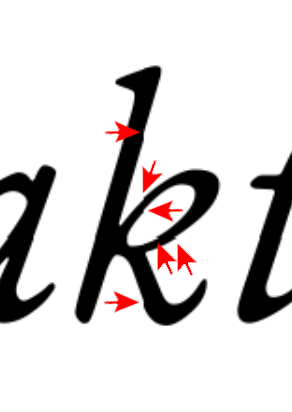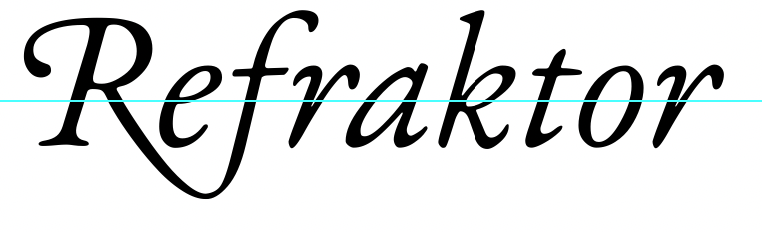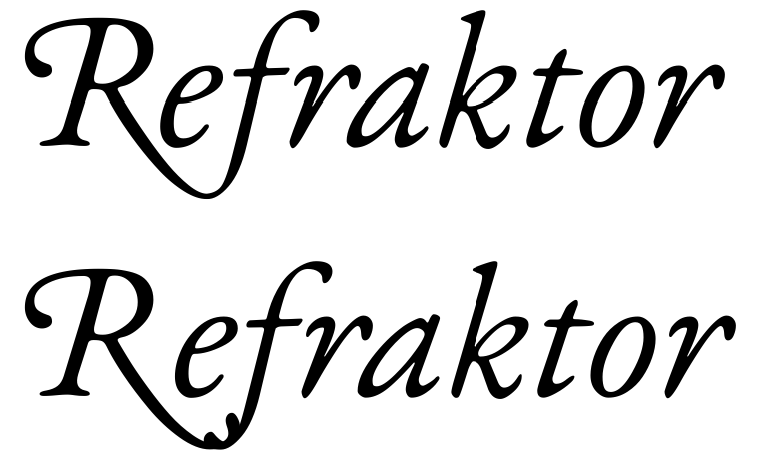
Ligatur über einen Buchstaben hinweg - geht sowas?
Ich bin bei einem Layout-Projekt auf ein interessantes Problem gestoßen. Ich setze in EBGaramond, habe für den Kursivsatz die geschwungenen Versalienvarianten gewählt und da kommen sie bei den Wörtern "Reflektor" und "Refraktor" das lange Bein des geschwungenen "R" und das kleine "f" in die Quere. Das sieht dann aus wie unten dargestellt.
Gelöst habe ich das Problem, indem ich fürs Erste für diese Konstellation das geschwungene "R" durch das normale kursive "R" ersetzt habe. Trotzdem gefiele mir die Idee einer eigenen Ligatur aus geschwungenem kursiven "R" und dem kursiven kleinen "f", die um das "e" herum geführt wird. Frage in die Runde: Gibt es sowas? Ist sowas denkbar? Oder sollte man sowas tunlichst bleiben lassen? Der EBGaramond-Code würde zumindest theoretisch zulassen, dass man so etwas zusammenbaut. Im Grunde müsste man nur dafür Sorgen, dass die Enden der Bögen des "R"-Fußes und des "f" miteinander verschmelzen.
Grundsätzlich sind Schwungbuchstaben bei dieser Größe / innerhalb des Lesetextes keine gute Idee - die sind zum Schmuck an ausgewählten Stellen da wo es passt, nicht um sie überall pauschal einzusetzen.
Das gesagt: Opentype erlaubt keine Ligaturen mit "Wildcard" dazwischen, also sowas wie R?f  und beim ? kann dann beliebig was stehen, geht nicht (oder nur mit viel viel Hirnlego). Aber man könnte natürlich mehrere Ligaturen anlegen, die wahrscheinlich vorkommen, also schöne Raf, Ref, Rif, Rof, Ruf, ..., und dann die Abfolge der drei Zeichen durch die jeweilige Ligatur ersetzen.
Eine Option wäre es, mit Kontext-Ersetzung statt Ligaturen zu arbeiten:
Wenn Swash aktiviert ist, und einem R ein beliebiges Zeichen folgt, und dann ein f, dann wird statt dem normalen swash-R eine Alternative verwendet, die NICHT mit dem f kollidiert. Oder aber so überlappt, dass sich eine schöne Form ergibt (schwierig, weil verschieden breite Zeichen dazwischen stehen können).
Man muss entsprechende Klassen bilden und mehrere Stellen nach vorn schauen. Habe genau dies bei meiner FDI Wunder gemacht:
Der Schwung des R ist so lang, dass man mindestens zwei Stellen nach vorn schauen muss. Kommen an Position zwei oder drei Lettern mit Unterlänge (aus der entsprechenden Glyphenklasse), greift die Schwungform nicht.
Zwei kurze Punkte dazu: Mir ist klar, dass man sowas nicht im Brottext macht. Ich nutze kursiv für Auszeichnungen. Das zitierte Beispiel ist wörtliche Rede eines Lehrers, der die Begriffe "Refraktor" und "Reflektor" gerade zum ersten Mal vor seinen Schülern benutzt. Ich erlaube mir im kursiven Text ein bisschen Schmuck (neben den geschwungenen Versalien auch die st-Ligatur), auf den ich im Brottext bewusst verzichte.
Ich hatte gar nicht darüber nachgedacht, eine Ligatur mit Wildcard anzulegen. Die Zwischen R und f werden im Deutschen nur Vokale stehen und die sind in EB Garamond unterschiedlich breit. Deswegen müsste man das selbstverständlich für jeden Fall neu basteln. Meine Idee wäre im Wesentlichen, eine passende Variante des geschwungenen R und des f zu schaffen, die dann mit dem e dazwischen die Ligatur bilden. Andere entsprechende Zusammensetzungen kommen in dem Text, den ich gerade setze, nicht vor.
Ich habe jetzt mal ein paar Stunden rumgefrickelt und erstmal das R und die fl-Ligatur entsprechend bearbeitet. Für das Wort "Reflektor" kommt da schon etwas sehr brauchbares raus, finde ich. Wenn man stärker reinzoomt, sind dort noch Brüche zu erkennen, die man ggf. noch versuchen müsste, rauszunehmen, aber das ist im Detail sicher sehr mühsam, weil ich dafür am EBGaramond-Quellcode arbeite und die Spline-Sätze von Hand bearbeite. Ich habe jetzt auch keine "Ref"-Ligatur erstellt, sondern ich habe eigene Versionen des "R" und der "fl"-Ligatur erstellt.
Dafür, dass ich sowas noch nie vorher gemacht habe, bin ich für Erste erstmal zufrieden.
So sieht das Ergebnis aus:
Hallo @Dirwani: Deine Überlegung ist interessant. Aber ich stelle mir die ernsthafte Frage, ob das nicht zu einem Großteil an der "fl"-Ligatur liegt.